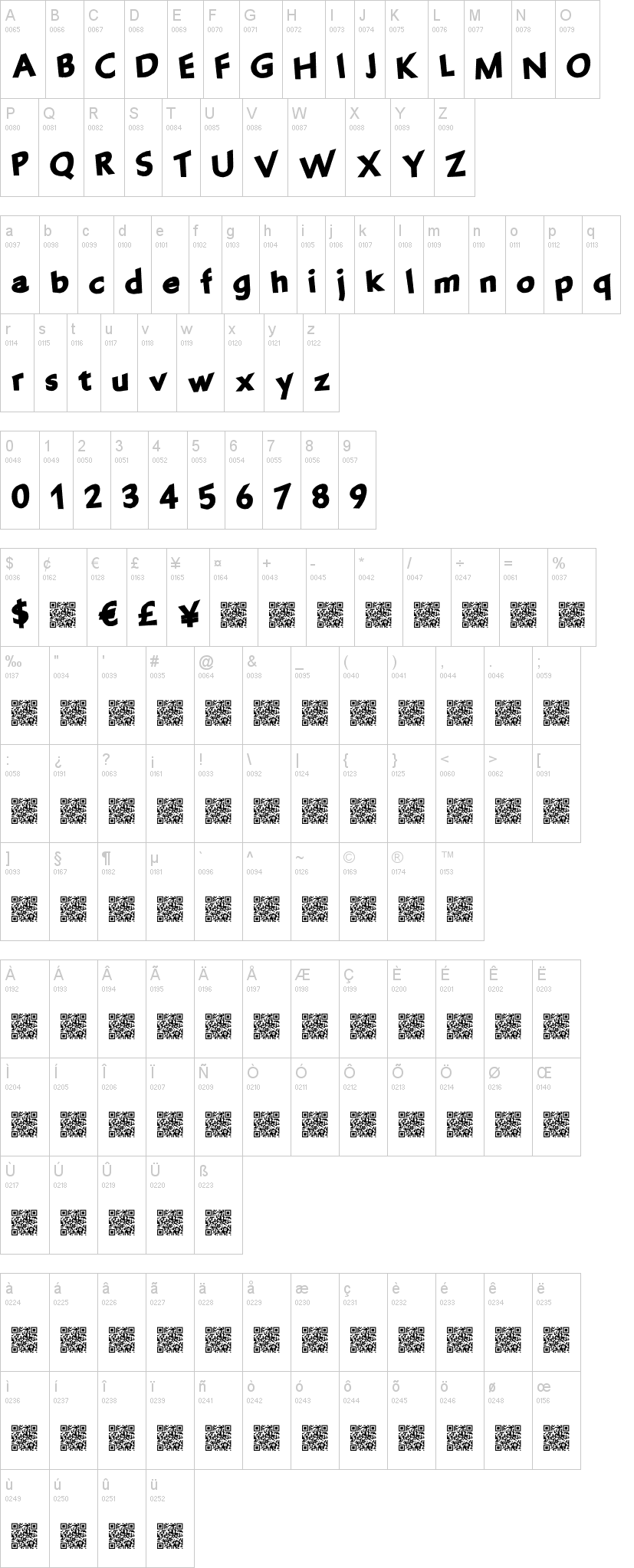
Fantastic Party是一种非常流行的手写风格字体,它的风格有点像卡通或漫画风格。这种字体的特点是笔画粗细不一,字母间距较小,有很强的视觉冲击力和可读性。 Fantastic Party字体常用于海报设计、广告宣传、卡片制作、电影标题等场合。它能够营造出非常欢快、轻松、愉悦的氛围。 如果您需要使用Fantastic Party字体,您可以在互联网上搜索并下载免费或付费的字体文件。在安装字体文件之后,您就可以在设计软件中选用它来制作您的作品。内容介绍
Fantastic Party是一款非常不错的手写艺术字体,具有很好的视觉感,适合于文化类的宣传设计、商业类品牌的广告和产品包装设计以及个性化文字排版等较多场景。